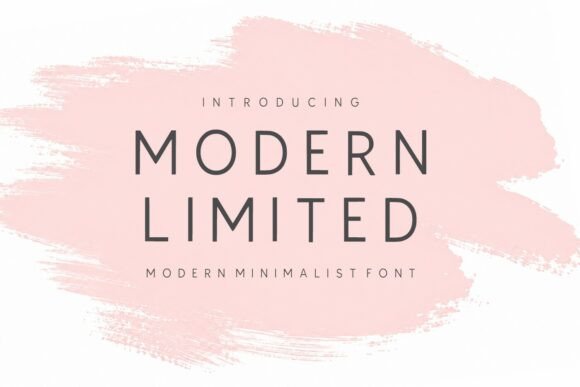
Modern Limited
Modern Limited – Le choix incontournable pour un design minimaliste & luxueux
Vous cherchez une police qui allie élégance, lisibilité et modernité ? Modern Limited répond à toutes ces exigences. Conçue spécialement pour les créatifs qui souhaitent projeter une image premium, cette police sans‑serif minimaliste devient rapidement le pilier de toute identité visuelle contemporaine.
Pourquoi Modern Limited séduit les designers
- Design épuré – Lignes nettes et proportions équilibrées qui garantissent une lecture fluide, même à petite taille.
- Inspiration luxe – Influencée par le branding haut de gamme, les magazines de mode et l’architecture moderne, elle confère immédiatement une aura de prestige.
- Polyvalence – Parfaite pour les titres imposants comme pour le corps de texte, elle s’adapte aux supports imprimés et digitaux.
- Adaptabilité sectorielle – Idéale pour les marques de beauté, les labels de mode, les agences d’architecture, les portfolios photo, les invitations de mariage et la communication corporate.
- Optimisation SEO – Son rendu net améliore le temps de chargement des pages web, favorisant ainsi le référencement naturel.
Applications concrètes
Voici quelques usages où Modern Limited fait toute la différence :
- Création de logos premium – des formes nettes qui restent mémorables.
- Design de sites web – typographie responsive qui conserve sa clarté sur tous les écrans.
- Packaging haut de gamme – un rendu élégant qui attire le regard en rayon.
- Contenus pour les réseaux sociaux – des titres percutants qui boostent l’engagement.
- Présentations professionnelles – une lecture agréable qui renforce la crédibilité.
Le verdict des experts
Modern Limited n’est pas simplement une police : c’est une déclaration de style. Sa géométrie propre et son charme contemporain offrent une toile de fond idéale pour toute communication cherchant à se démarquer avec sophistication. Que vous soyez une agence de branding, un créateur freelance ou une grande entreprise, cette police vous aidera à créer des identités visuelles mémorables tout en respectant les meilleures pratiques SEO.
Conclusion
En résumé, Modern Limited représente le summum du minimalisme luxueux. Sa capacité à s’adapter à divers supports, combinée à une lisibilité optimale, en fait le choix stratégique pour quiconque veut projeter une image moderne, professionnelle et exclusive. N’attendez plus : intégrez Modern Limited à vos projets et laissez chaque caractère raconter votre histoire avec élégance.